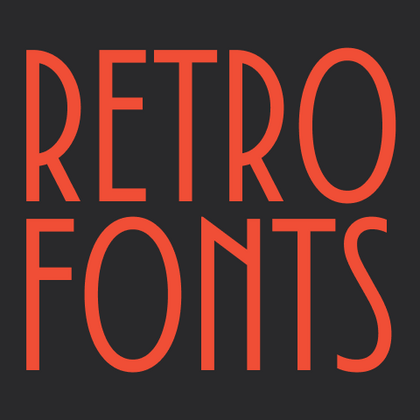
TT Chocolates — изящный гуманистический гротеск сo сбалансированными пропорциями, близкими к классическим. Шрифт с приятным дружелюбным характером, который интуитивно воспринимается как что-то знакомое.
Ретро шрифты
Если вы хотите придать вашему проекту ностальгическое настроение, либо стилизовать его под винтажный стиль, для этой цели подойдут ретро шрифты. Это шрифты в стиле второй половины XIX — первой половины XX века. При этом главное преимущество современных шрифтов в ретро стиле заключается в том, что они функциональны, а также выглядят свежо и стильно. Изучите ретро-шрифты из коллекции TypeType.
TT Modernoir — акцидентный гротеск с разноширинными пропорциями. Плавные линии и изящные формы ар-нуво в этом шрифте сочетаются с ритмичностью и импровизационной свободой джаза.
TT Moons — узкая и контрастная антиква. Данное шрифтовое семейство очень элегантно работает в классических темах дизайна. TT Moons по стилистике относится к глиптальным новостильным шрифтам. Идеальная сфера использования TT Moons — это верстка журналов, книг и газет.
TT Lakes Neue в версии 2.0 — продолжение геометрического гротеска, вдохновлённого финским функционализмом. Новая версия предоставляет больше возможностей, ведь мы не только увеличили кассовый состав и улучшили шрифт технически, но и доработали его визуальный характер.
TT Trailers — стильный и выразительный акцидентный гротеск. Его легко узнать по необычной графике: рисунок каждого знака в этом шрифте авторский, формы экспериментальные. Он гармонично смотрится в оформлении афиш и плакатов, идеально подходит для оформления титров. Однако на практике сфера применения этой гарнитуры гораздо шире.
TT Backwards Sans — это узкий гротеск, пластичностью своих знаков отсылающий нас в книжное оформление конца 70-х — начала 80-х годов и выполненный с учетом использования в маленьком размере текста. Магазинные вывески, постеры и плакаты, книжное оформление — вот где мы черпали вдохновение для нашего проекта.
TT Knickerbockers Grotesk символизирует собой монументальность, выраженную в как в традиционной исторической застройке Нью-Йорка, так и в его небоскрёбах. Энергия, постоянное движение и круглосуточная жизнь Нью-Йорка — все это отразилось в нашем TT Knickerbockers Script.
TT Polls берет свое начало как современный модульный брусковый шрифт. При создании шрифтового семейства TT Polls мы держали в голове его использование в дизайне на спортивную тематику, но финальная версия TT Polls отлично подходит и для более казуального дизайна и сфер применения.
TT Berlinerins — это контрастная пара шрифтов, которая по сути является нашим трибьютом Берлину. Также, как и в самом городе переплетаются историчность и современность, так и в нашем шрифтовом семействе элегантный скрипт символизирует собой современный Берлин, а гротеск, выполненный в стиле плакатных wood-type шрифтов первой трети 20-го века, отвечает за историческую составляющую города.
Первоначально идея шрифтового семейства TT Milks заключалась в том, чтобы создать коллекцию шрифтов для использования в упаковке и брендинге молочной продукции.
TT Corals — это современный гуманистический гротеск, который имеет очень много характерных исторических черт начала 20-го века. Шрифт хорошо подойдет для темы классической литературы или музыки, а также для других самых разнообразных творческих областей человечества.
TT Octas — шрифтовое семейство с узкими пропорциями, построенное по принципу октагональности, в данной гарнитуре все окружности представляют из себя восьмигранники. Благодаря небольшим засечкам Октас приобретает насыщенный и старинный характер.